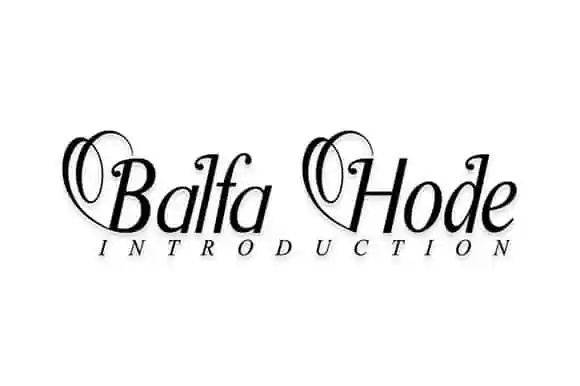
BalfaHode Serif Font é uma escolha perfeita para quem busca adicionar sofisticação aos seus projetos digitais e impressos. Esta fonte serifa não apenas oferece um toque elegante para textos de grande dimensão, como os cartazes em parede ou as imagens de produtos, mas também se adapta com fluidez a anúncios, embalagens de produtos, etiquetas, logotipos de mídias sociais e até mesmo às resenhas dos clientes, tudo isso sem perder a sua elegância. Seja para criar um design minimalista ou adicionar detalhes luxuosos aos seus materiais impressos, esta fonte é uma opção ideal, permitindo que você mantenha sempre o seu estilo pessoal e sofisticado no centro das atenções.